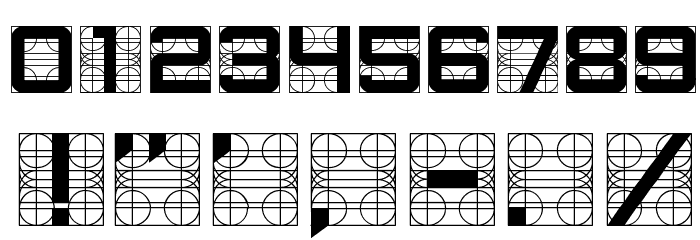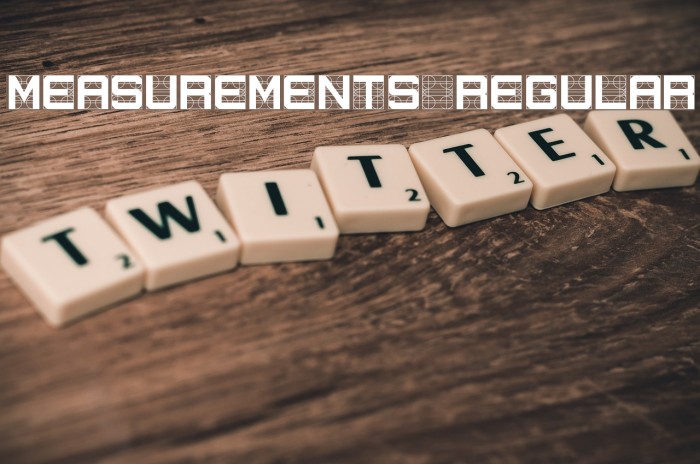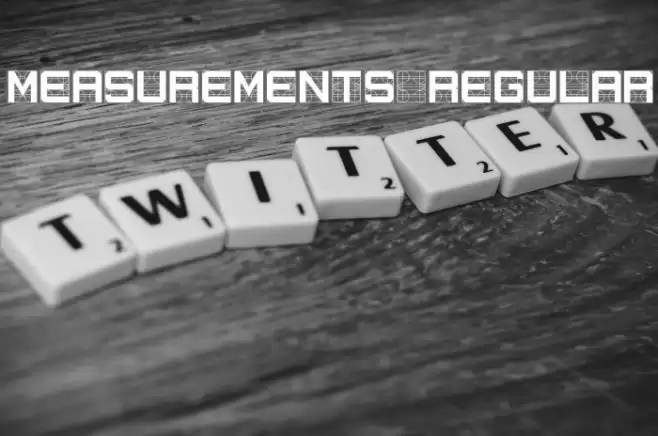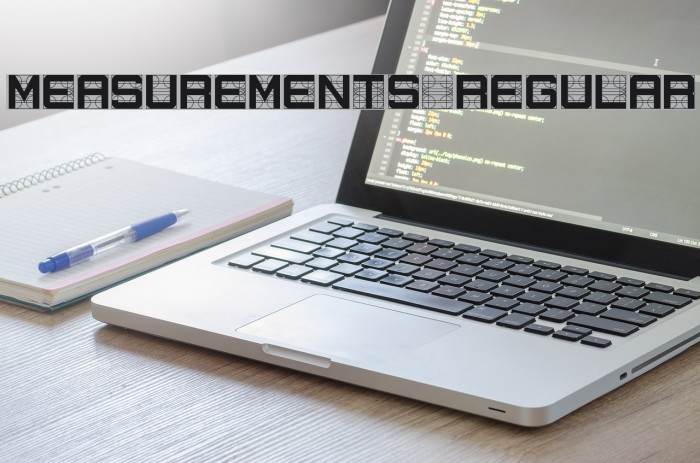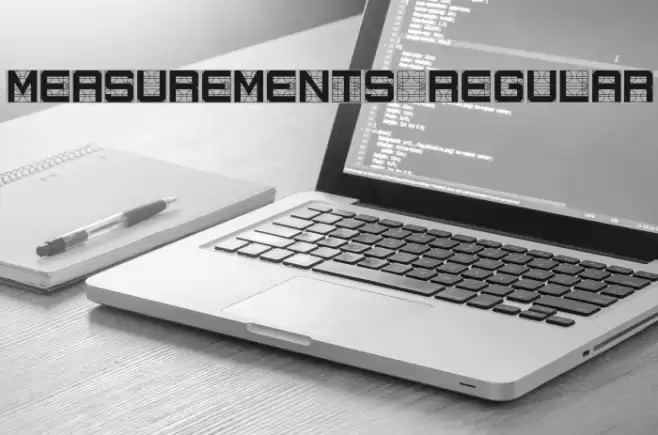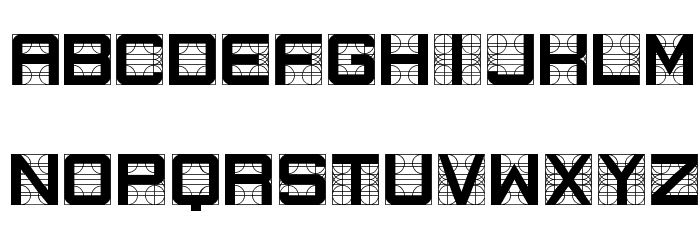
Measurements Regular Font
| Proiecte propuse | Ideal for architectural branding, engineering presentations, tech-themed posters, and futuristic design projects. |